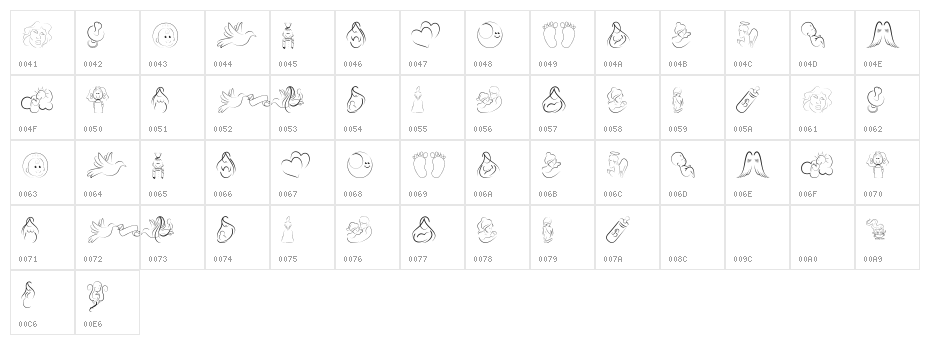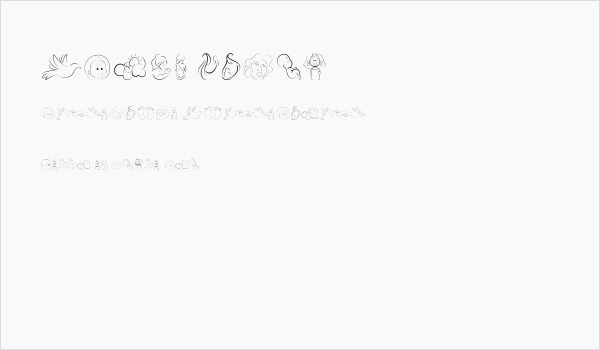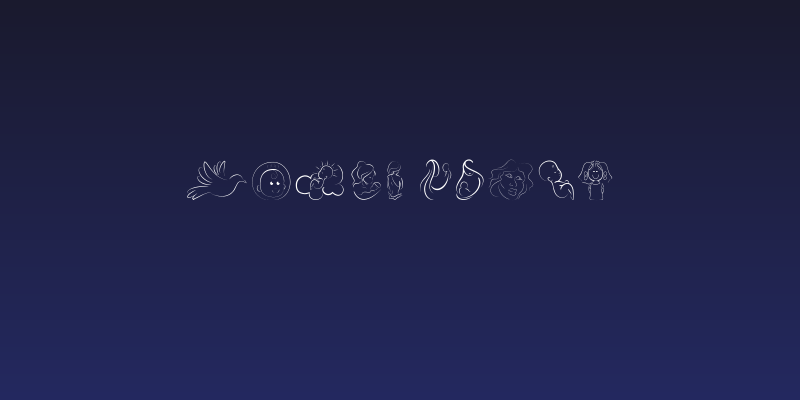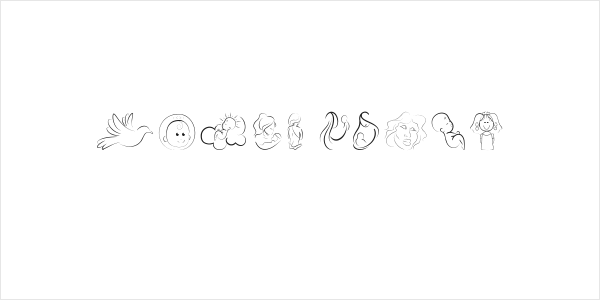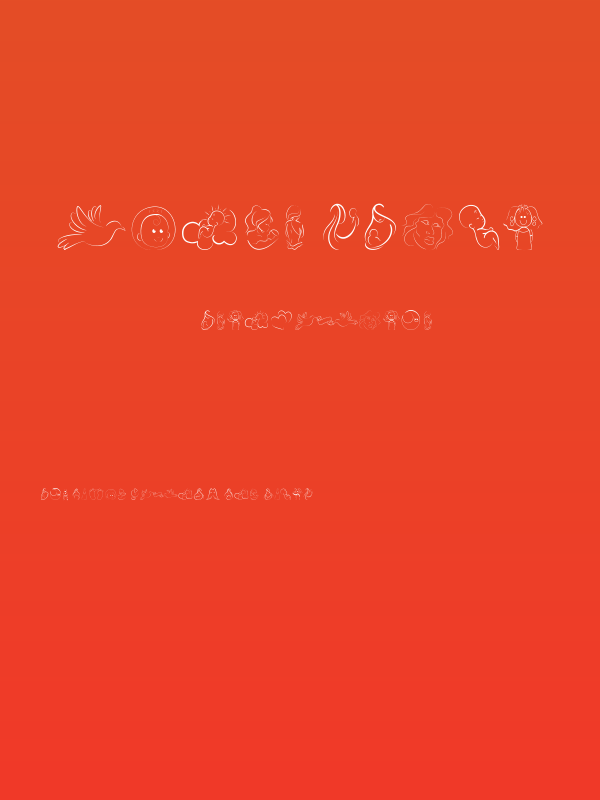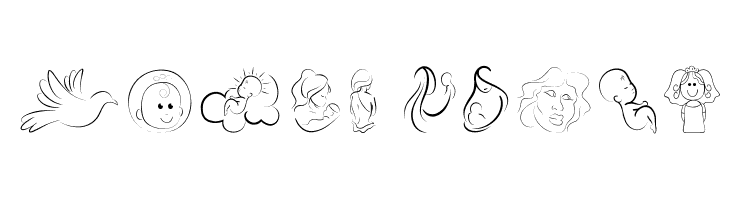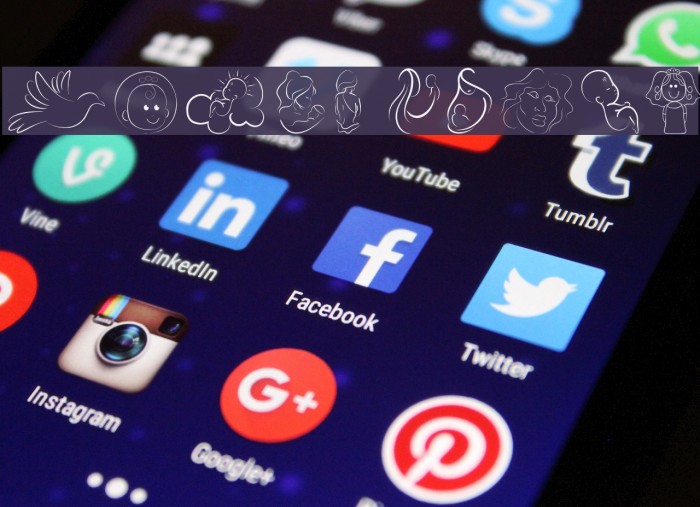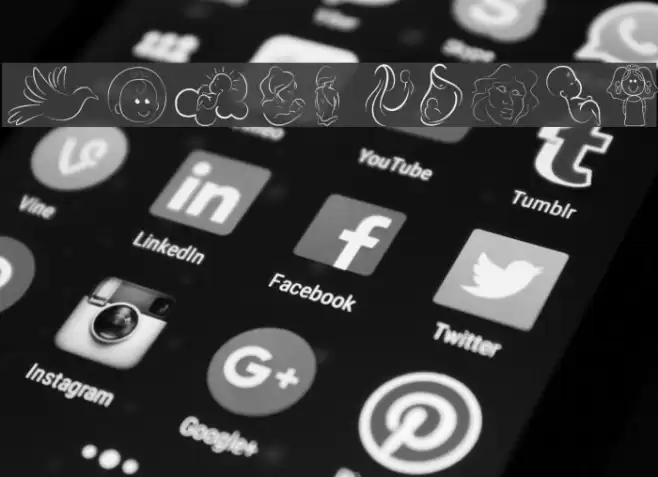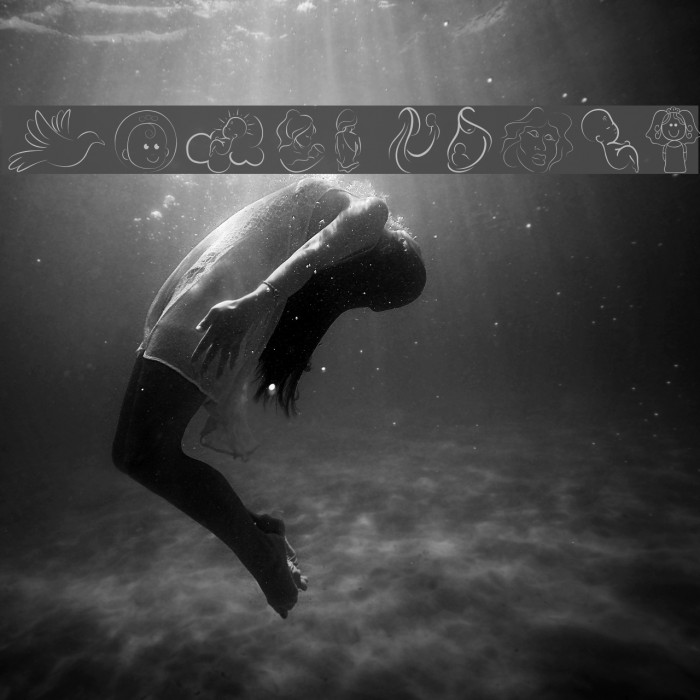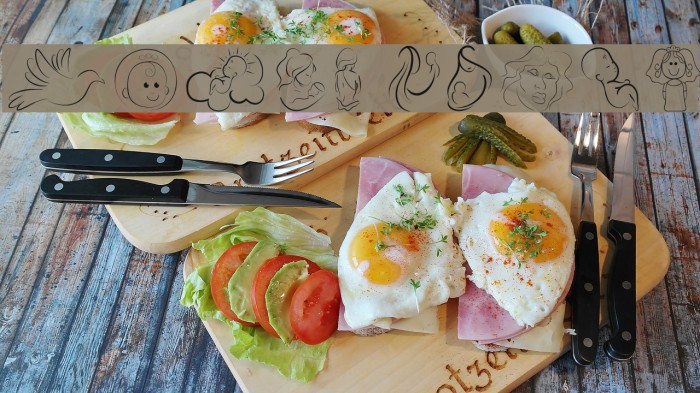
DCOXY stamp Font
✎ Dingbats
| Stil general | Decorative, Playful, Whimsical |
| Caz de utilizare | Icons, Decorative elements, Themed graphics |
| Proiecte propuse | Children’s books, baby shower invitations, greeting cards, playful branding, educational materials. |